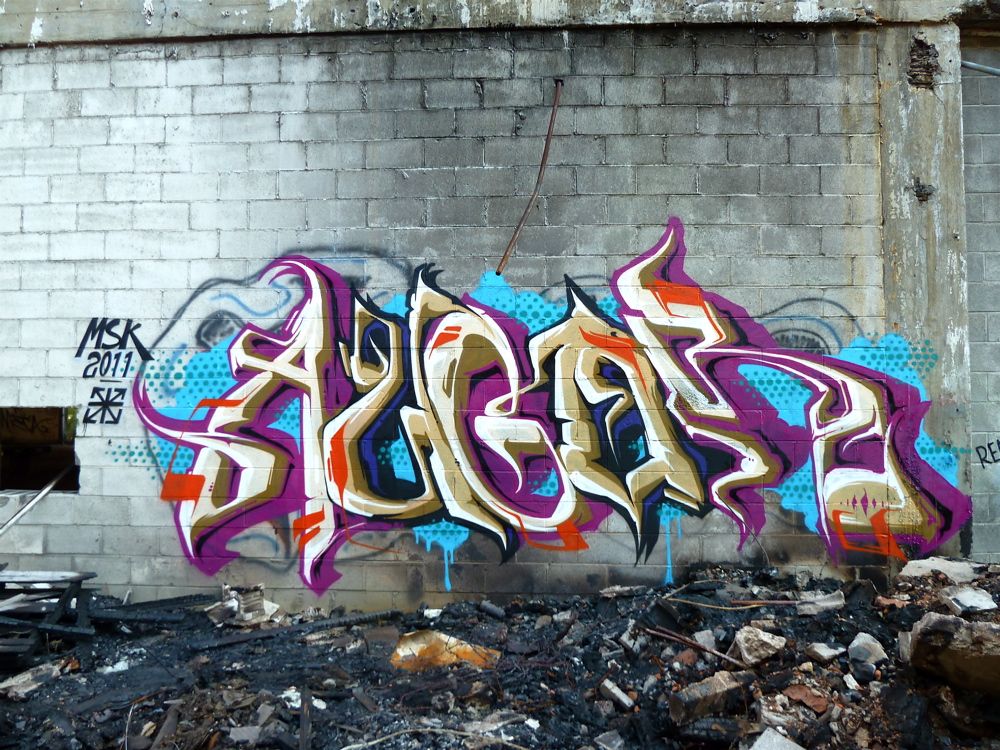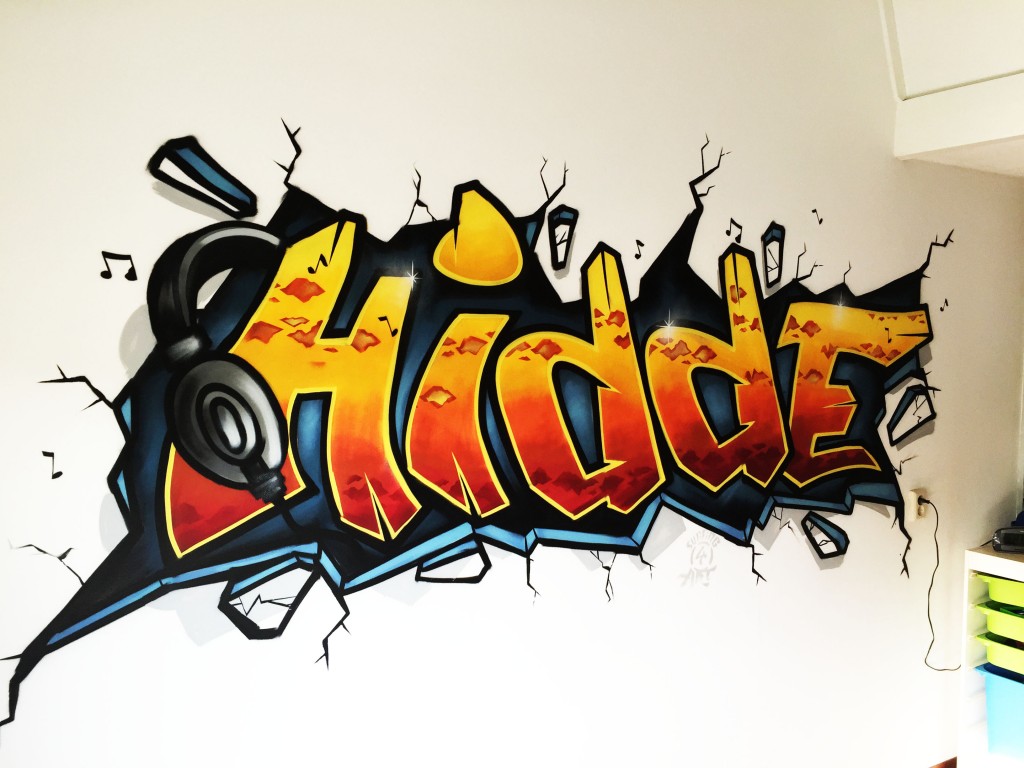
1. Граффити
2. Граффити
3. История
Настенные надписи известны с глубокой древности, ониоткрыты в странах Древнего Востока, в Греции, в Риме.
Значение этого слова со временем стало обозначать любую
графику, нанесенную на поверхность и расцениваемую
многими как акт вандализма.
Древний мир
Самые ранние граффити появились в 30 тысячелетии до н.
э.Тогда они были представлены в форме
доисторических настенных крисунков и пиктографий,
нанесенных на стены такими инструментами, как кости
животных. Подобные рисунки часто делались в ритуальных и
священных местах внутри пещер. Чаще всего на них
изображали животных, живую природу и сцены охоты. Эта
форма граффити нередко вызывает споры, насколько
вероятно, что подобные изображения создавались именно
членами доисторического общества.
4. Средние века
Граффити были широко распространены в доколумбовой Месоамерике.В одном из крупнейших городищ майя Тикаль было обнаружено
множество хорошо сохранившихся рисунков. Граффити викингов,
уцелевшие в Риме и в Ирландии , а также знаменитая надпись варяга,
нацарапавшего своё имя (Халвдан) рунами на перилах в Софийском
соборе в Константинополе, — все эти граффити помогают нам узнать
некоторые факты из повседневной жизни прошлых культур. Граффити,
известные как Тахеронс, нередко находят на стенах в романскоскандинавских церквях.
Средневековые граффити на Руси
У восточных славян граффити имеют долгую и богатую историю.
В Новгороде сохранилось 10 граффити XI века. Большое число, около 300
граффити XI—XV веков имеется в соборе св. Софии в Киеве, содержащих
как рисунки, так и (чаще) текст. Они повествуют о политических событиях
прошлого, упоминают исторические лица: князя Ярослава Мудрого, его
сыновей Святослава и Всеволода, внуков Святополка и Владимира
Мономаха, епископа Луку Белгородского, воеводу Ставра Горядитинича и
других. Наиболее ранние надписи дали возможность исследователям
уточнить время сооружения собора и выполнения его внутренней отделки.
Также древнерусские граффити выявлены на стенах памятников
архитектуры Киева: Кирилловской церкви, Михайловского собора
Выдубицкого монастыря и некоторых киевских Пещер. Около 1915 года в
Киеве был найден фрагмент корчаги с граффити XI века, ныне
хранящейся в Историческом музее.
5. Средние века
6.
Современная истоияСчитается, что граффити тесно связано с брейк-данс-культурой итем бесчисленным количеством стилей, которые произошли от ньюйоркского граффити в метрополитене. Несмотря на это,
существует много других замечательных примеров граффити. В
начале XX века граффити стали появляться в товарных вагонах и
подземных переходах. Один из таких граффити — Texino — ведёт
свою историю с 1920-х годов до нашего времени.Вскоре после
смерти Чарли Паркера граффити со словами «Bird Lives» стали
появляться по всему Нью-Йорку. В ходе студенческих протестов и
всеобщей забастовки в мае 1968 года в Париже город оказался
наводнен революционными, анархистскими и ситуационистскими
лозунгами, такими как, которые были выполнены в стиле
граффити, плаката и трафаретногискусства. В это время в США на
короткий период становятся популярными политические слоганы
(такие как «Освободите Хьюи», посвященные Хьюи Ньютону.